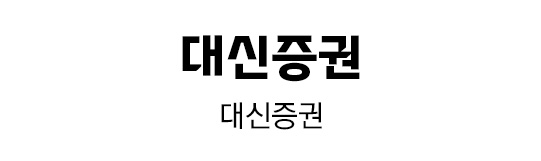
기존 독창적인 대신증권만의 아이덴티티는 유지하되 아이덴티티 재점검을 통해 완성도를 높인 서체로 새롭게 태어난 대신증권 전용서체는 제목용과 본문용으로 나누어 굵기 연구를 통해 8종으로 사용할 수 있습니다.
| 프로젝트명 | 대신증권 전용서체 'Daishin Text, Daishin Title' |
| 스펙 | 한글 2,780자 / 영문 94자 / 약물 986자 / 8종 |